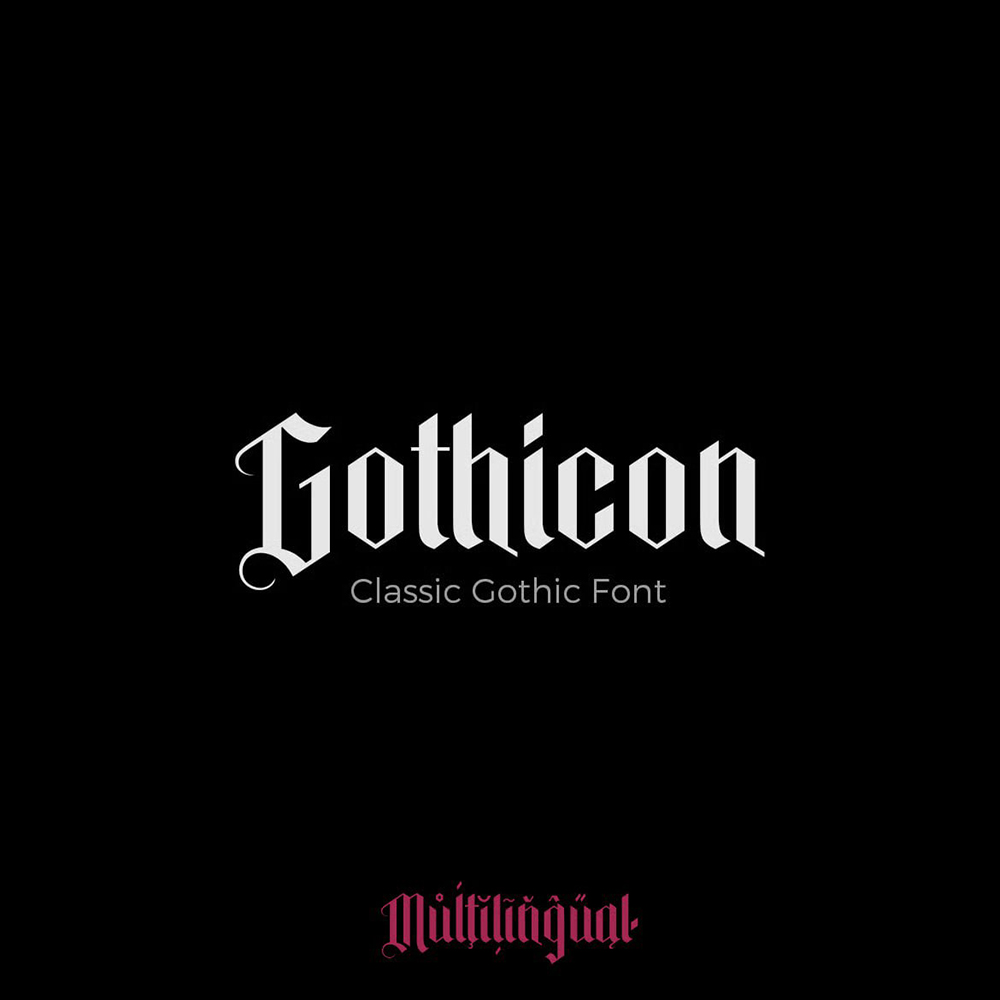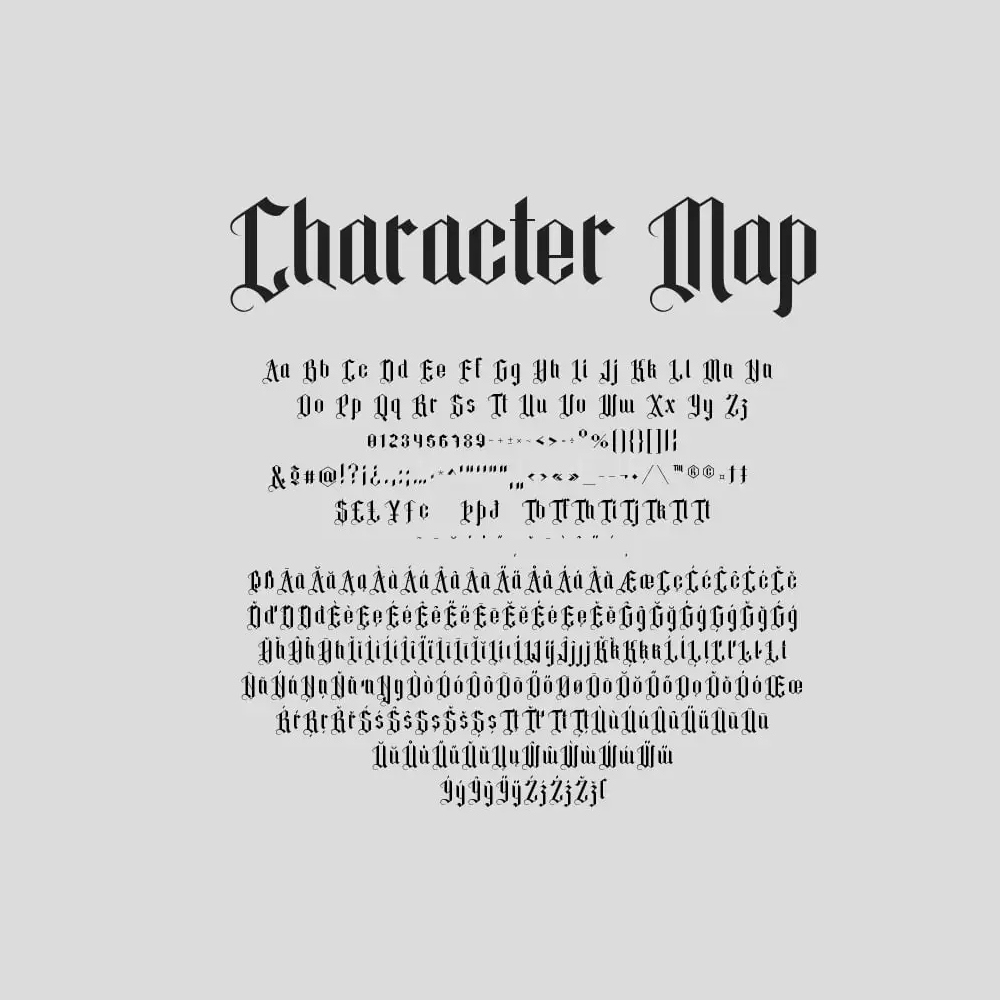
دانلود فونت انگلیسی Gothicon Font
فونت پرمیوم و انگلیسی Gothicon Font یک فونت اصیل، کلاسیک، وینتج و از نوع گوتیک بلکلتر است. این فونت مناسب برای استفاده در پوستر، لیبلها و بجهای وینتج، تیتر، بستهبندی و بسیاری موارد دیگر میباشد.
مزایای استفاده از فونت لاتین Gothicon چیست؟